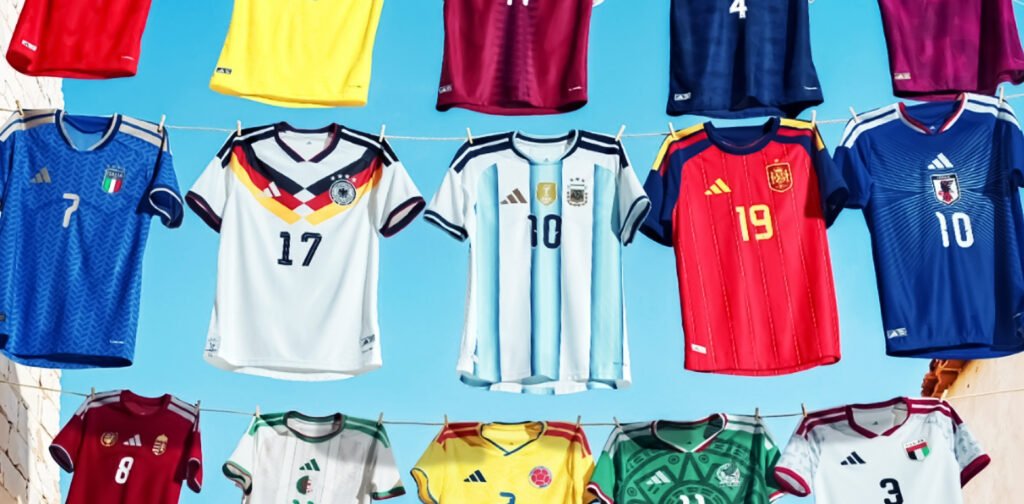
Cuma Ganti Font, Tampilan Desain Langsung Naik Level
Font desain printing apparel adalah salah satu elemen yang paling sering diabaikan, padahal pengaruhnya terhadap tampilan akhir produk sangat besar. Kebanyakan orang langsung fokus ke warna, gambar, atau layout saat membicarakan desain sementara typography justru sering dianggap sepele.
Padahal kenyataannya, desain yang awalnya terasa biasa saja bisa langsung terlihat lebih mahal dan premium hanya karena mengganti jenis font yang digunakan. Hal ini sangat sering terjadi di dunia printing dan desain apparel ada desain sederhana yang begitu typography-nya pas, tampilannya langsung terasa profesional. Sebaliknya, ada juga desain dengan konsep yang bagus namun hasil akhirnya kurang “dapet” hanya karena font yang dipilih tidak sesuai karakter desain.
Itulah mengapa sekarang banyak brand mulai lebih serius memperhatikan typography sebagai bagian dari identitas visual produk mereka. Menurut Adobe, typography yang tepat mampu meningkatkan persepsi nilai sebuah produk secara signifikan bahkan sebelum konsumen membaca isinya.
Banyak Orang Fokus ke Warna, Padahal Font Desain Printing Apparel Juga Sangat Menentukan
Font desain printing apparel punya karakter yang berbeda-beda, ada yang terlihat tegas, ada yang elegan, ada yang santai dan modern. Saat font diganti, suasana keseluruhan desain pun ikut berubah drastis.
Contoh nyatanya pada jersey: jika menggunakan font sporty dengan garis tegas, tampilan langsung terasa lebih aktif dan berani. Namun jika diganti dengan font tipis dan clean, kesannya berubah menjadi lebih premium dan modern padahal elemen desain lainnya tidak berubah sama sekali.
Banyak orang baru menyadari pentingnya font setelah membandingkan dua desain yang isinya identik tetapi menggunakan typography berbeda. Hasilnya selalu jelas mana yang lebih enak dilihat dan terasa lebih bernilai.
Karena itu, font bukan sekadar pelengkap. Dalam banyak desain apparel modern, typography justru menjadi salah satu elemen utama yang menentukan kualitas visual produk.
Tren Font Desain Printing Apparel Kini Bergeser ke Clean dan Minimalis
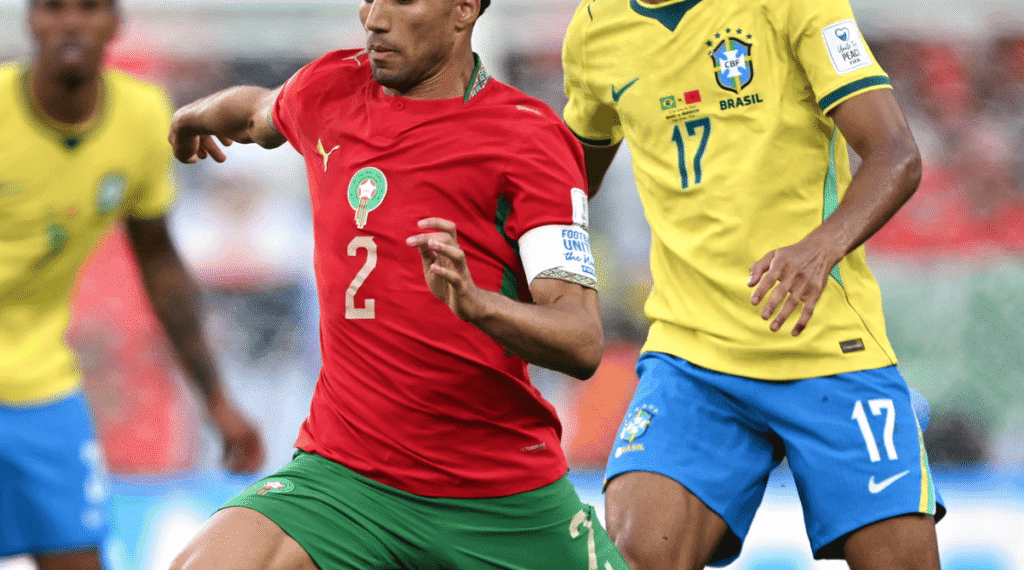
Kalau diperhatikan, tren font desain printing apparel saat ini memang mengalami pergeseran signifikan. Dulu desain penuh efek, warna ramai, dan banyak ornamen dianggap keren. Kini tren justru bergerak ke arah yang jauh lebih clean.
Brand-brand apparel modern sekarang lebih memilih:
- Font simpel dengan karakter yang kuat
- Layout rapi dan terstruktur
- Warna lebih bersih dan terseleksi
- Detail tipis yang tetap tajam
- Typography modern yang timeless
Alasannya sederhana, tampilan clean lebih nyaman dilihat dan terasa lebih premium. Dan justru karena desainnya simpel, detail kecil seperti pemilihan font menjadi jauh lebih menonjol dan menentukan. Peran typography dalam font desain printing apparel kini jauh lebih penting dibanding sebelumnya. Baca juga:15 Inspirasi Desain Kaos Custom dengan Perpaduan Font dan Grafis yang Keren
Typography Jadi Identitas Visual dalam Font Desain Printing Apparel Modern
Font desain printing apparel kini bukan lagi sekadar tulisan biasa. Banyak brand ternama menggunakan typography sebagai identitas visual utama mereka bahkan ada desain yang hampir tidak menggunakan ilustrasi sama sekali, hanya mengandalkan permainan font dan layout.
Pendekatan ini sering terlihat pada:
- Jersey modern dan football apparel
- Clothing brand streetwear lokal dan internasional
- Konten media sosial dan kampanye visual
- Desain merchandise dan packaging produk
Karena setiap karakter font membangun kesan yang berbeda:
- Font bold → kesan kuat, tegas, berani
- Font clean → kesan premium, modern, elegan
- Font futuristik → kesan teknologi, forward-looking
- Font sporty → cocok untuk apparel olahraga dan jersey
Itulah mengapa pemilihan font desain printing apparel kini menjadi keputusan strategis, bukan sekadar pilihan estetika.
Kesalahan Font Desain Printing Apparel yang Masih Sering Terjadi
Walaupun terlihat sederhana, memilih font desain printing apparel yang tepat ternyata tidak semudah yang dibayangkan. Masih banyak desain yang sebenarnya sudah bagus, tetapi jadi kurang maksimal karena typography-nya kurang tepat.
Kesalahan yang paling sering terjadi:
- Terlalu banyak jenis font dalam satu desain membuat tampilan jadi ramai dan tidak fokus
- Font sulit dibaca terutama untuk nomor punggung dan nama pemain pada jarak jauh
- Ukuran tulisan tidak proporsional sehingga hierarki visual jadi kacau
- Terlalu banyak efek tambahan seperti shadow, outline, dan glow yang berlebihan
- Font tidak sesuai konsep desain misalnya font playful di jersey olahraga serius
Padahal desain clean dengan font desain printing apparel yang tepat justru jauh lebih profesional dibanding desain yang terlalu ramai elemen.
Pengaruh Font Desain Printing Apparel pada Produk Jersey
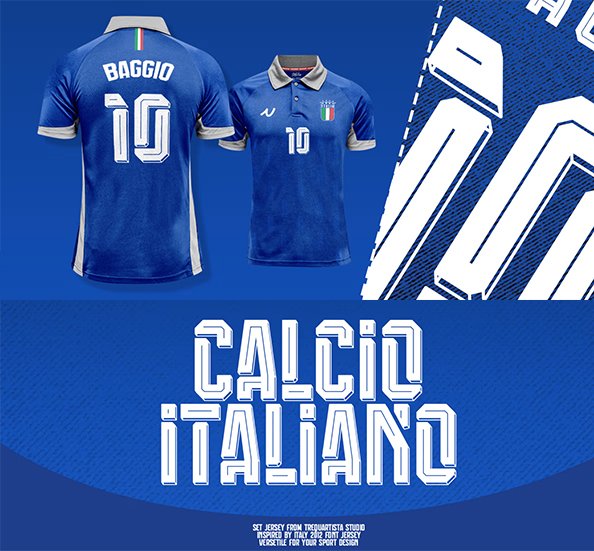
Di dunia jersey printing dan apparel, typography punya pengaruh langsung yang sangat besar terhadap tampilan produk jadi. Mulai dari:
- Nomor punggung dan nama pemain
- Tulisan sponsor dan logo komunitas
- Detail identitas tim atau brand
- Typography utama desain jersey
Kalau font desain printing apparel yang dipakai kurang cocok, desain jersey bisa langsung terasa biasa dan tidak berkarakter. Itulah mengapa desain jersey modern kini banyak menggunakan typography clean dan futuristik agar tampilannya terasa lebih premium dan kompetitif di pasar.
Font Bagus Harus Didukung Mesin Printing yang Tepat
Satu hal penting yang sering dilupakan: font bagus di layar belum tentu bagus saat dicetak. Dalam produksi printing, detail typography harus tetap keluar dengan rapi saat masuk ke proses produksi terutama untuk desain yang menggunakan:
- Garis tipis dan detail kecil
- Huruf berukuran kecil
- Efek gradasi pada typography
- Typography clean dengan presisi tinggi
Jika mesin printing kurang stabil, font akan terlihat pecah, buram, atau kurang tajam dan dapat langsung merusak tampilan keseluruhan produk.
Karena itu sekarang banyak pelaku usaha printing semakin serius memilih mesin produksi yang mampu menjaga detail font desain printing apparel tetap maksimal dari layar hingga menjadi produk jadi.
Rhinotec: Mesin yang Menjaga Detail Font Desain Printing Apparel Tetap Tajam
Untuk memastikan font desain printing apparel tetap tampil maksimal saat diproduksi, pemilihan mesin yang tepat adalah investasi yang tidak bisa dikompromikan.
Rhinotec menyediakan berbagai solusi mesin yang dirancang untuk menjaga detail typography tetap tajam dan konsisten:
Untuk kebutuhan sublimasi jersey full color: Rhinotec GT i190S dikenal karena hasil warnanya yang stabil dan kemampuannya menjaga detail desain termasuk typography tipis dan desain modern full color agar tetap keluar dengan sempurna.
Untuk kebutuhan DTF custom apparel: Mesin DTF Rhinotec series hadir dalam berbagai pilihan yang dapat disesuaikan dengan skala produksi, dari UMKM hingga industri volume tinggi dengan keunggulan:
- Hasil warna tajam dan solid
- Detail typography kecil tetap presisi
- Stabil untuk produksi harian intensitas tinggi
- Cocok untuk apparel custom dengan variasi desain beragam
Pelajari lebih lanjut: Tips Memilih Mesin Sublimasi Terbaik Sesuai Skala Produksi
Desain Modern Butuh Mesin Stabil untuk Hasil Font yang Konsisten
Pelanggan sekarang semakin kritis dalam menilai kualitas produk apparel. Mereka tidak hanya melihat desain secara umum, tetapi juga memperhatikan detail yang lebih kecil:
- Ketajaman tulisan dan typography
- Presisi garis-garis tipis pada font
- Kerapihan hasil print di setiap sudut
- Konsistensi warna dari satu produk ke produk berikutnya
- Finishing produk secara keseluruhan
Saat desain clean dan typography menjadi tren utama font desain printing apparel, detail kecil harus benar-benar dijaga agar hasil akhirnya tetap terlihat profesional. Inilah yang membuat banyak pelaku usaha mulai meng-upgrade mesin produksi mereka. Baca juga: Rahasia Hasil Cetak DTF yang Tajam & Tahan Lama: Ini Settingan yang Dipakai Profesional
Kesimpulan
Font desain printing apparel yang tepat memang bisa langsung membuat tampilan produk terasa lebih modern, clean, dan premium . Hanya dari perubahan kecil pada typography. Namun desain bagus tetap harus didukung hasil printing yang maksimal agar setiap detail tetap keluar dengan sempurna saat diproduksi.